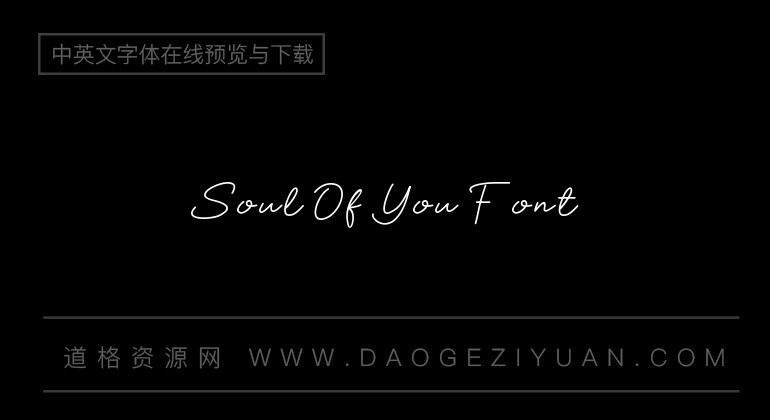
Soul of You是一种优雅的手写字体,它具有流畅的连笔和舒适的风格。字体包含大写字母、小写字母、数字和标点符号,适用于多种设计项目,如卡片、包装、书籍封面、海报、标题等。Soul of You字体为您的设计带来了一种自然和有机的感觉,适合用于传达真诚、温暖和体贴的情感。内容介绍
Soul Of You Font是一款非常不错的手写艺术字体,具有很好的视觉感,适合于文化类的宣传设计、商业类品牌的广告和产品包装设计以及个性化文字排版等较多场景。